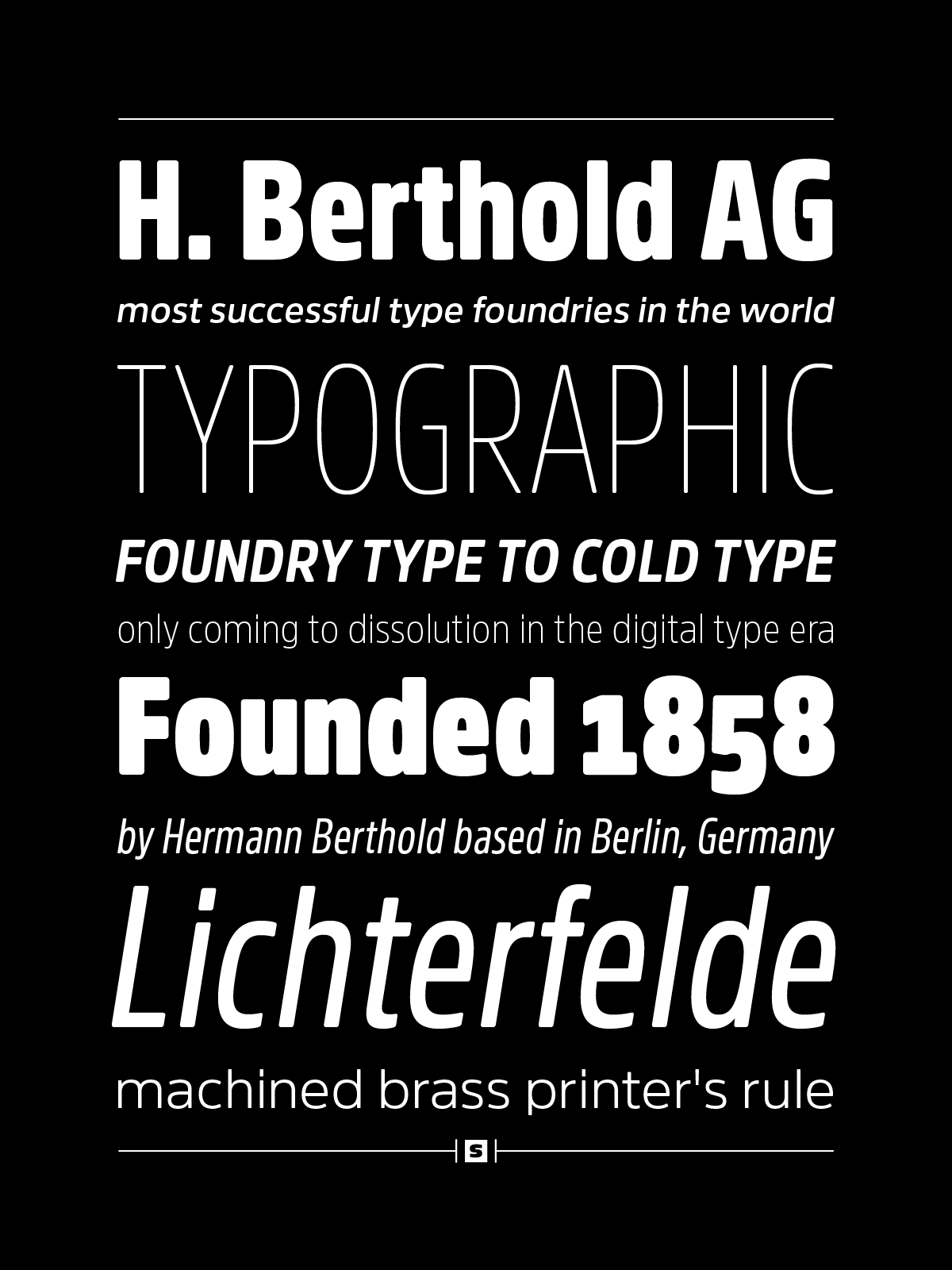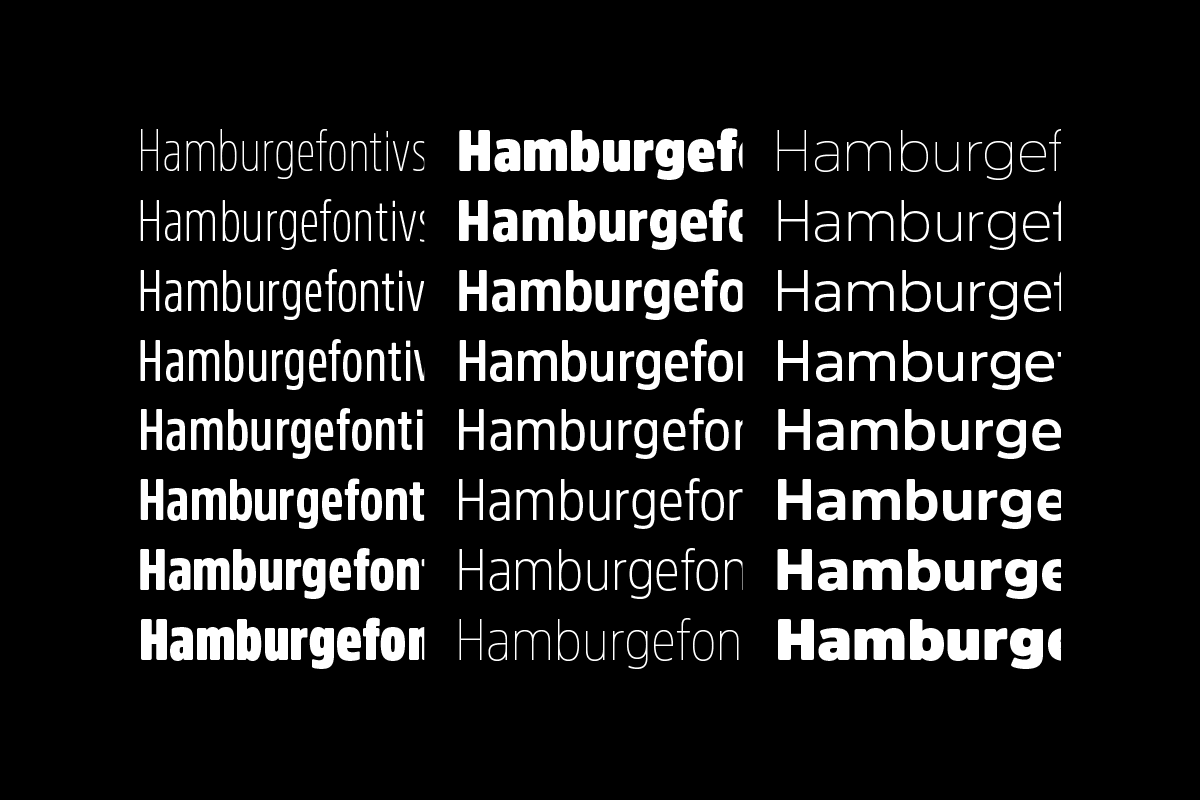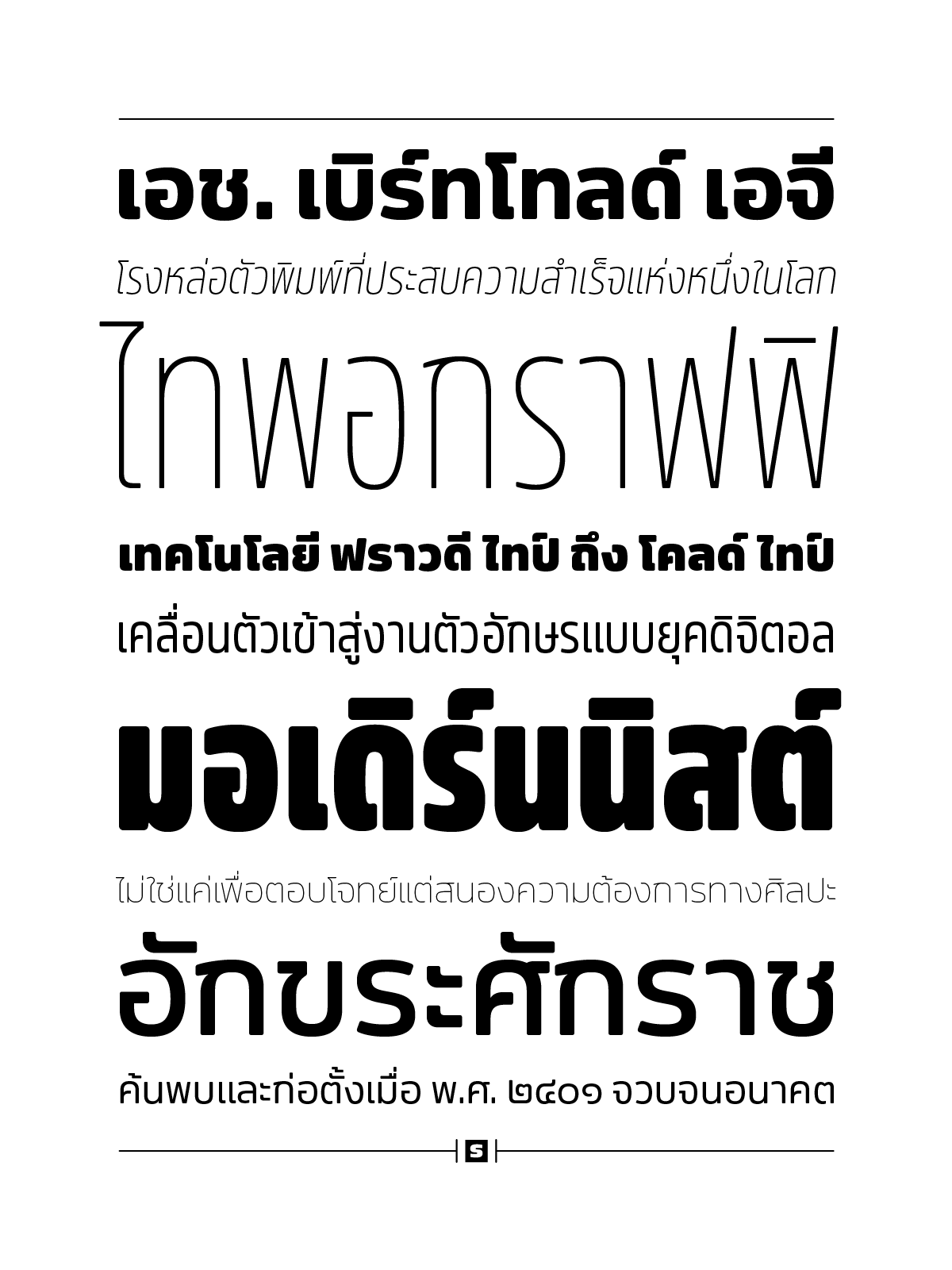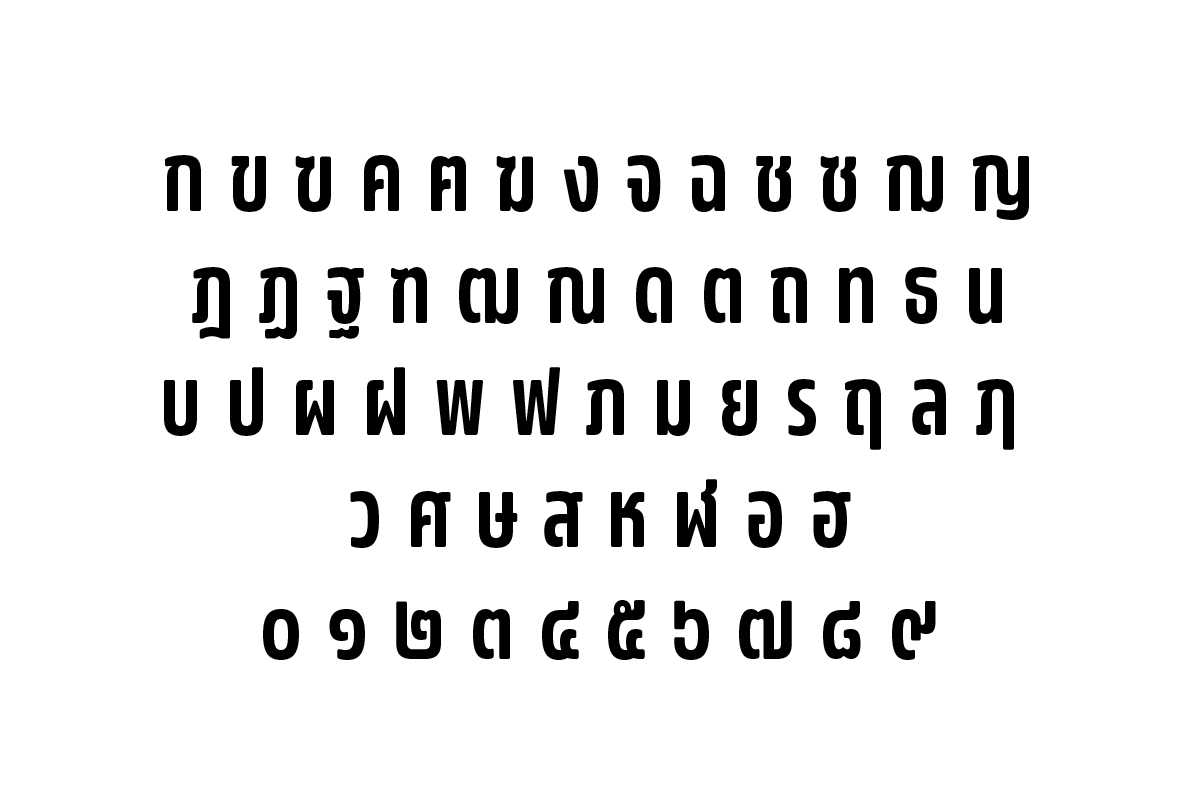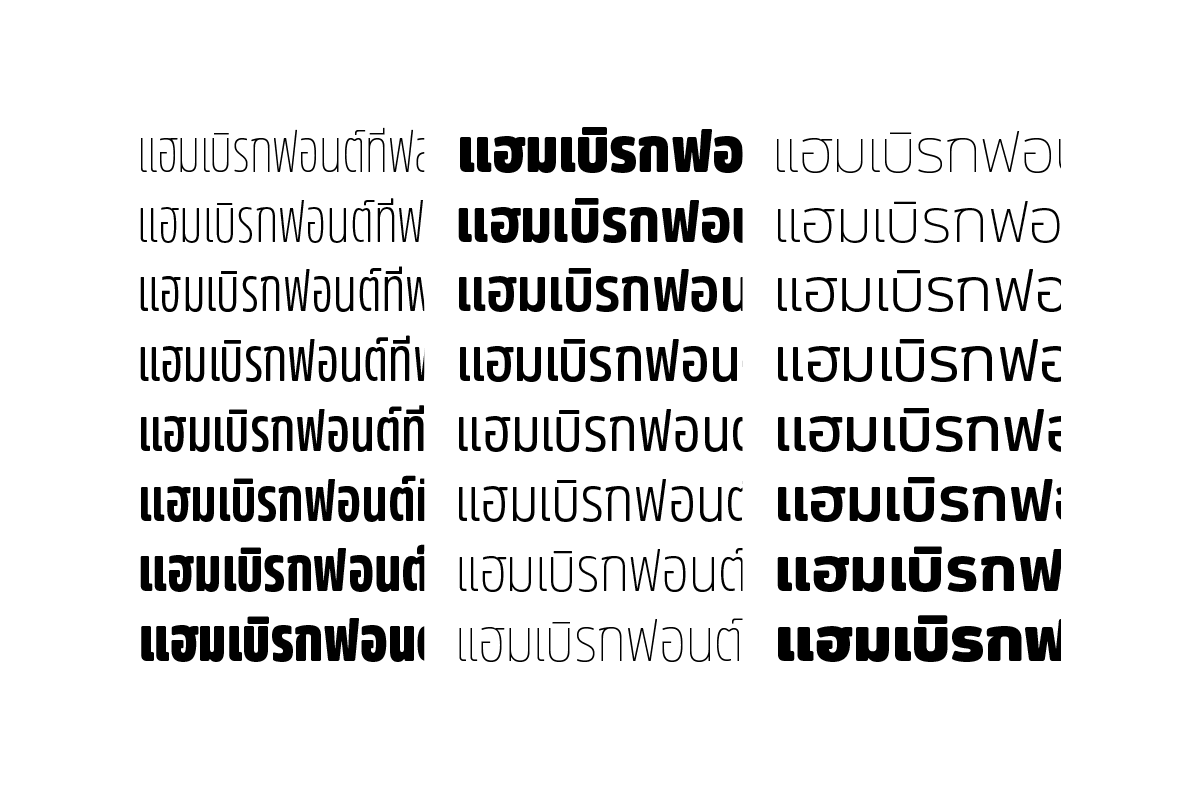
Amsi Pro AKS
แบบอักษร Amsi Pro AKS เน้นใช้งานในลักษณะของตัว Display ที่ใช้งานง่าย สบายตา ซึ่งในตัวของ latin นั้น ถือได้ว่าเป็น Font ที่ประสบความสำเร็จมากตัวหนึ่งของ ‘Stawix Foundry’ มาพร้อมกับ Feature มาตรฐานต่างๆ รองรับการใช้งานทุกรูปแบบเช่น สิ่งพิมพ์ เว็บ แอปฯ หรือ เซิร์ฟเวอร์ เป็นต้น มาพร้อมกับ 3 ความกว้าง ได้แก่ Condensed, Narrow และ Normal
Amsi has been designed to equipped with three different widths; Normal, Narrow and Condensed, addition to expanding weights to support various usabilities ranging from Thin, XLight, Light, Regular, SemiBold, Bold, Black and Heavy. Which makes Amsi along with a numerous features support the creativities of the designer from the Font Menu.
Designer : Stawix Chomvachara
Amsi Pro Specimen
Amsi Pro Alphabet
Amsi Pro Weight